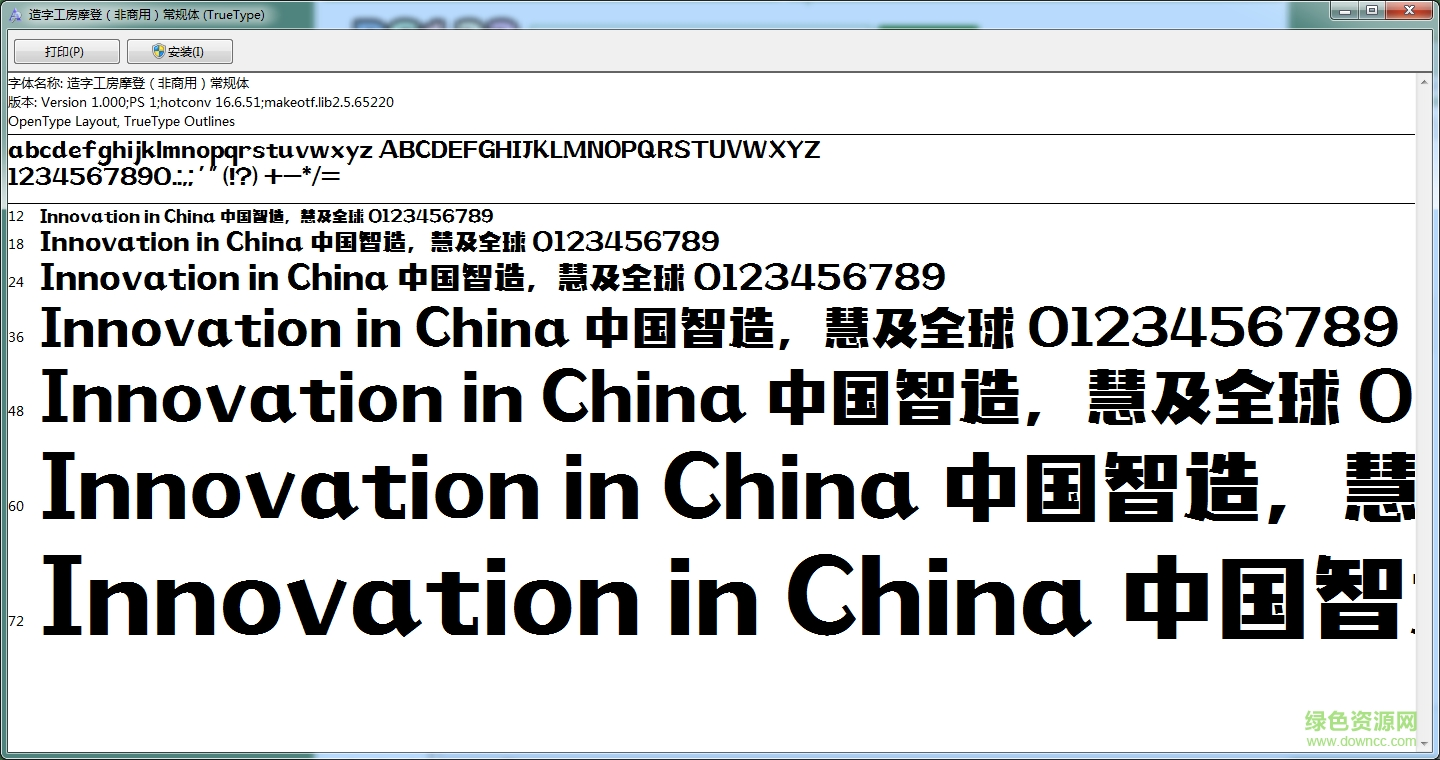
软件介绍 软件标签: 造字工房摩登体 造字工房 造字工房摩登体是一款端正美观的win字体,此款字体字型简洁,线条偏粗,具有引人注目的特点,拥有完整的字库,支持中文、英文、数字输入功能,应用范围非常广泛,喜欢的朋友欢迎来绿色资源网下载!字体安装方法方法一:控制面板/字体/文件/安装新字体;方法二:直接将字体复制到C:\WINDOWS\Fonts。方法三:针对win7系统,用户只需选中字体右键安装即可。注意事项本站所有字体资源仅供个人学习与参考,如需商业使用请到相关官网授权 软件截图 上一张下一张(1 / 1) 安装详细截图 其他版本下载 标题 大小 更新日期 下载 摩登课堂app v2.1.7.1 安卓版 16.07M 2018-09-01 下载 摩登大道手机版 v1.2.1 安卓版 8.58M 2017-02-06 下载 植物大战僵尸2摩登世界内购正式版 v2.2.0 安卓无限钻石版 910.94M 2023-03-19 下载 Modern摩登印 v1.1.2 安卓版 4.35M 2018-08-21 下载 友读小说 v2.2.8 安卓版 13.73M 2021-05-20 下载 小明进销存 v1.3.3 安卓版 4.88M 2019-03-30 下载 美萌360相机app v12 安卓版 47.05M 2022-05-19 下载 东方可儿摩登学园变态版 v2.0 安卓版 327.00M 2023-03-22 下载 摩登ONE v1.02 安卓版 25.20M 2018-03-08 下载 下载地址 电脑版 造字工房摩登体 点击报错 软件无法下载或下载后无法使用,请点击报错,谢谢! 关闭报错反馈 请描述您所遇到的错误,我们将尽快予以修正,谢谢! *必填项,请输入内容 本类最新 dreamweaver字体库 首尔南山体字体 v1.06 官方版 潮字社风云简ttf 潮字社凌渡鲲鹏简体字体 潮字社曾玉波手书简字体 微博慧心字体 用户评论 热门评论 最新评论 发表评论 查看所有评论(0) 昵称: 请不要评论无意义或脏话,我们所有评论会有人工审核. 字数: 0/500 (您的评论需要经过审核才能显示)